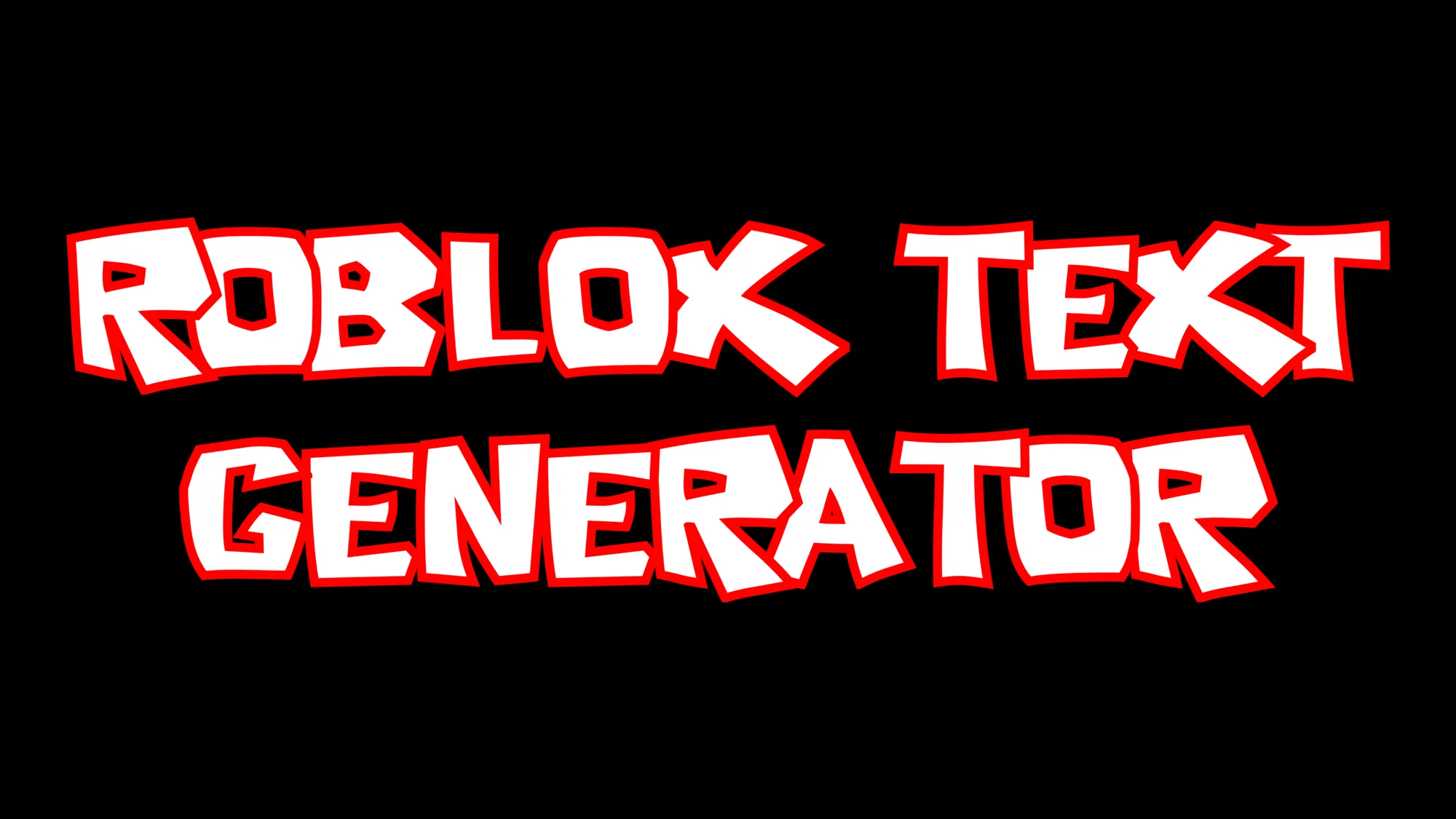
Il logo di Roblox è uno dei simboli più riconoscibili nel mondo dei videogiochi: deciso, divertente e pieno di energia. Con il giusto font Roblox e qualche effetto di testo creativo, puoi disegnare il tuo nome, logo o titolo nello stesso stile giocoso. Scopriamo insieme i design di testo ispirati a Roblox più popolari che puoi creare online.
Classico stile Roblox rosso
Il look classico di Roblox si distingue per le lettere bianche e spesse con un contorno rosso marcato. Questo stile del font del logo Roblox trasmette energia ed è immediatamente riconoscibile. È perfetto per banner, miniature di YouTube e loghi per i profili. Aggiungi un'ombra delicata o un contorno luminoso per dargli ancora più carattere.
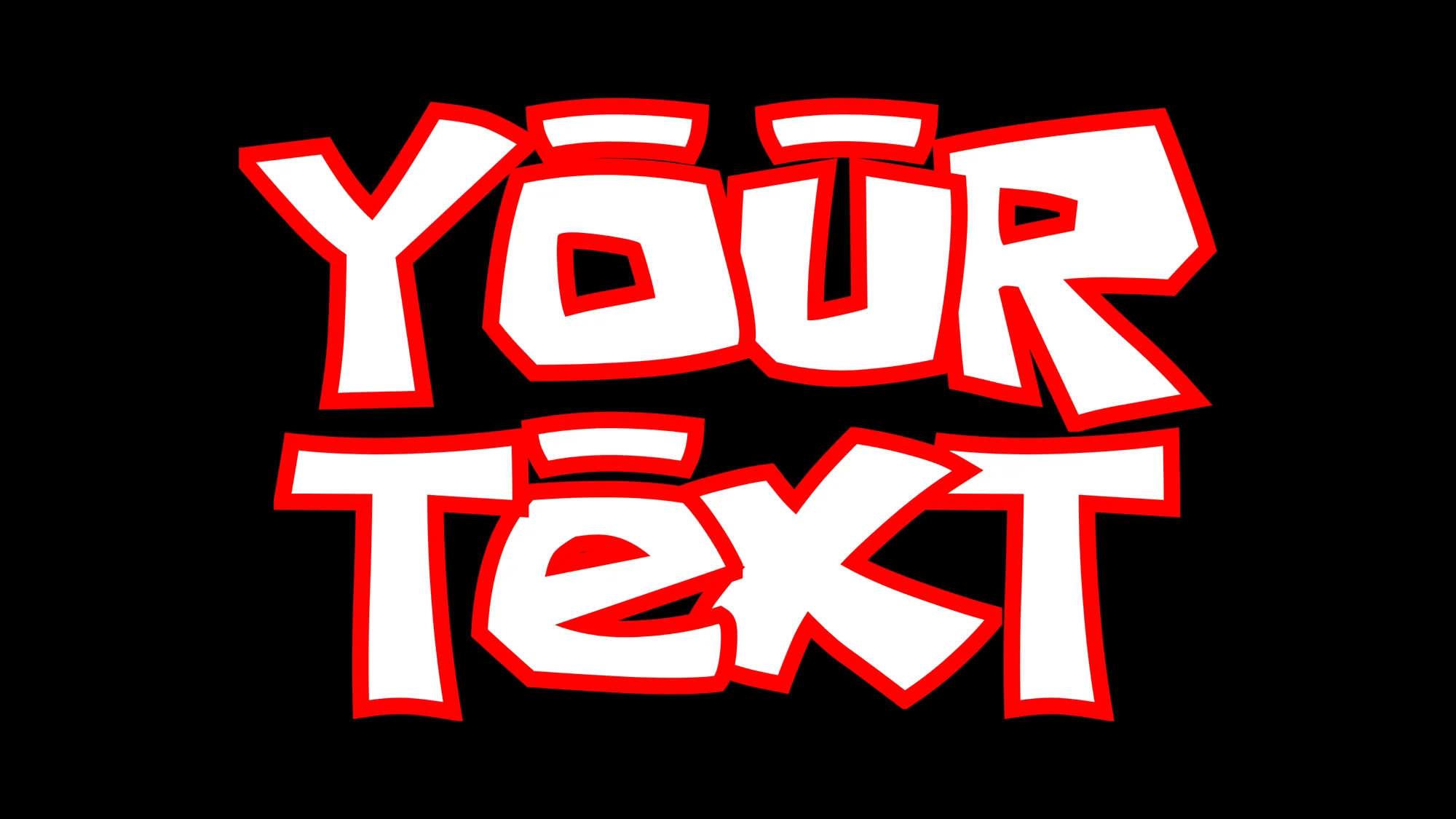
Che cos'era davvero il vecchio font di Roblox
Cerca il vecchio font di Roblox e troverai soprattutto file da scaricare, raramente una spiegazione. Eccola. Il logotipo del 2006 non è mai stato un font commerciale: era un lettering su misura, disegnato come logo e non come carattere, poi ripulito l'anno successivo in una versione vettoriale più ordinata. In seguito alcuni fan lo hanno ridisegnato e fatto circolare come file, da cui i nomi “2006 ROBLOX Logo” o semplicemente “Old Roblox Font”.
Questa storia spiega le forme. Un lettering da logo può permettersi di essere spesso, inclinato e un po' irregolare come nessun vero carattere potrebbe, perché doveva scrivere una sola parola. L'interfaccia è poi passata a un lineare geometrico pulito, ed è proprio questo contrasto a far leggere le forme antiche come retro.
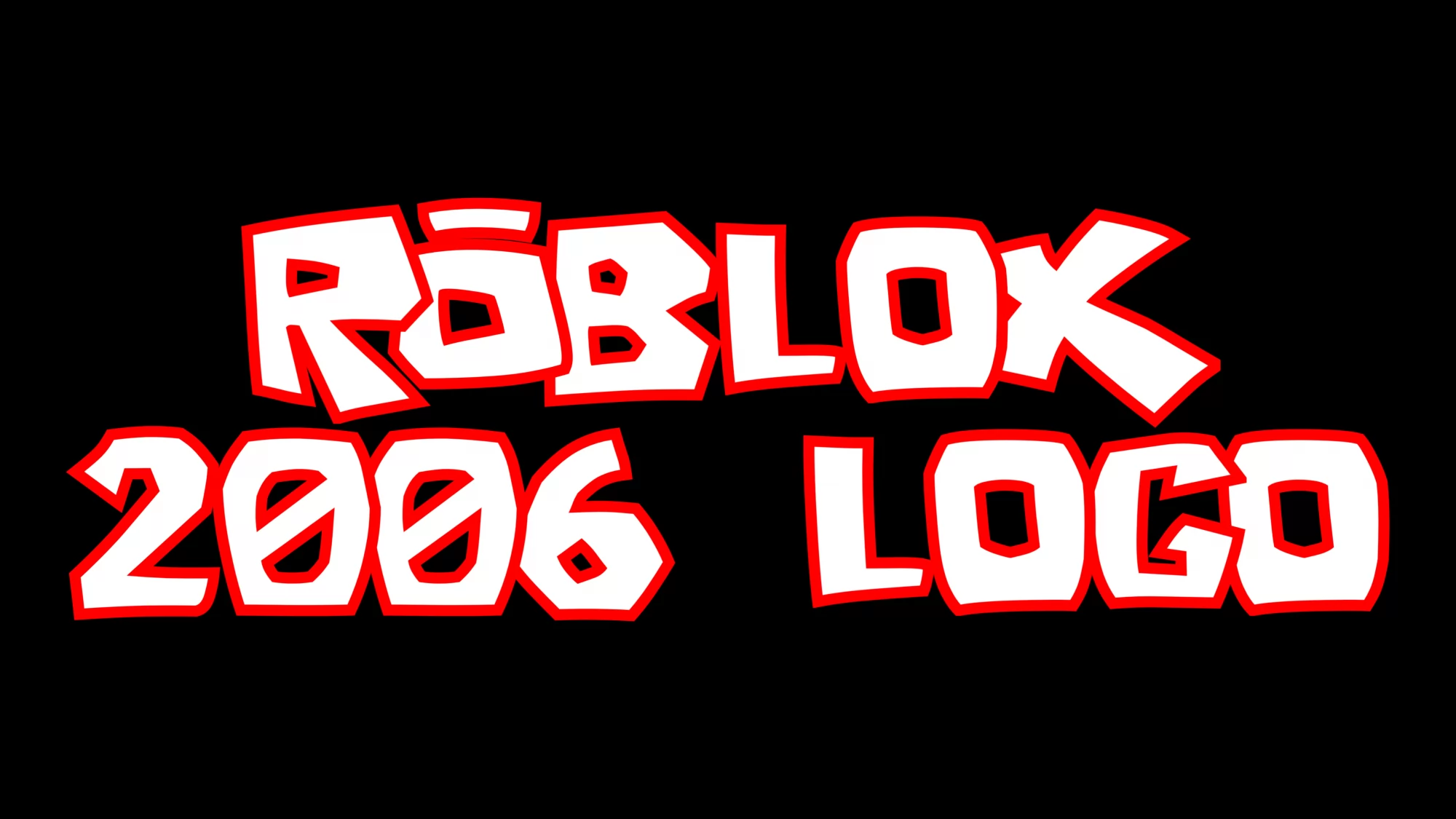
Non serve il file originale per ottenere l'effetto. Quattro cose lo reggono: lettere spesse che sembrano tracciate a mano più che composte, un contorno rosso robusto attorno a un riempimento bianco, linee di base che si rifiutano di restare dritte, e una leggera inclinazione su ogni carattere. Tieni il contorno spesso, perché è quel bordo rosso a tenere insieme le forme su uno sfondo affollato. Il generatore del logo 2006 monta tutti e quattro in un colpo solo.
Font Roblox 3D metallico
Per un effetto più moderno e curato, prova l'effetto di testo Roblox 3D. La finitura metallica e la leggera profondità rendono le lettere potenti e professionali, ideali per copertine di giochi, schermate introduttive o fan art. Abbina tonalità argento o grigie a sfondi blu acceso o rosso per richiamare i colori iconici del gioco.
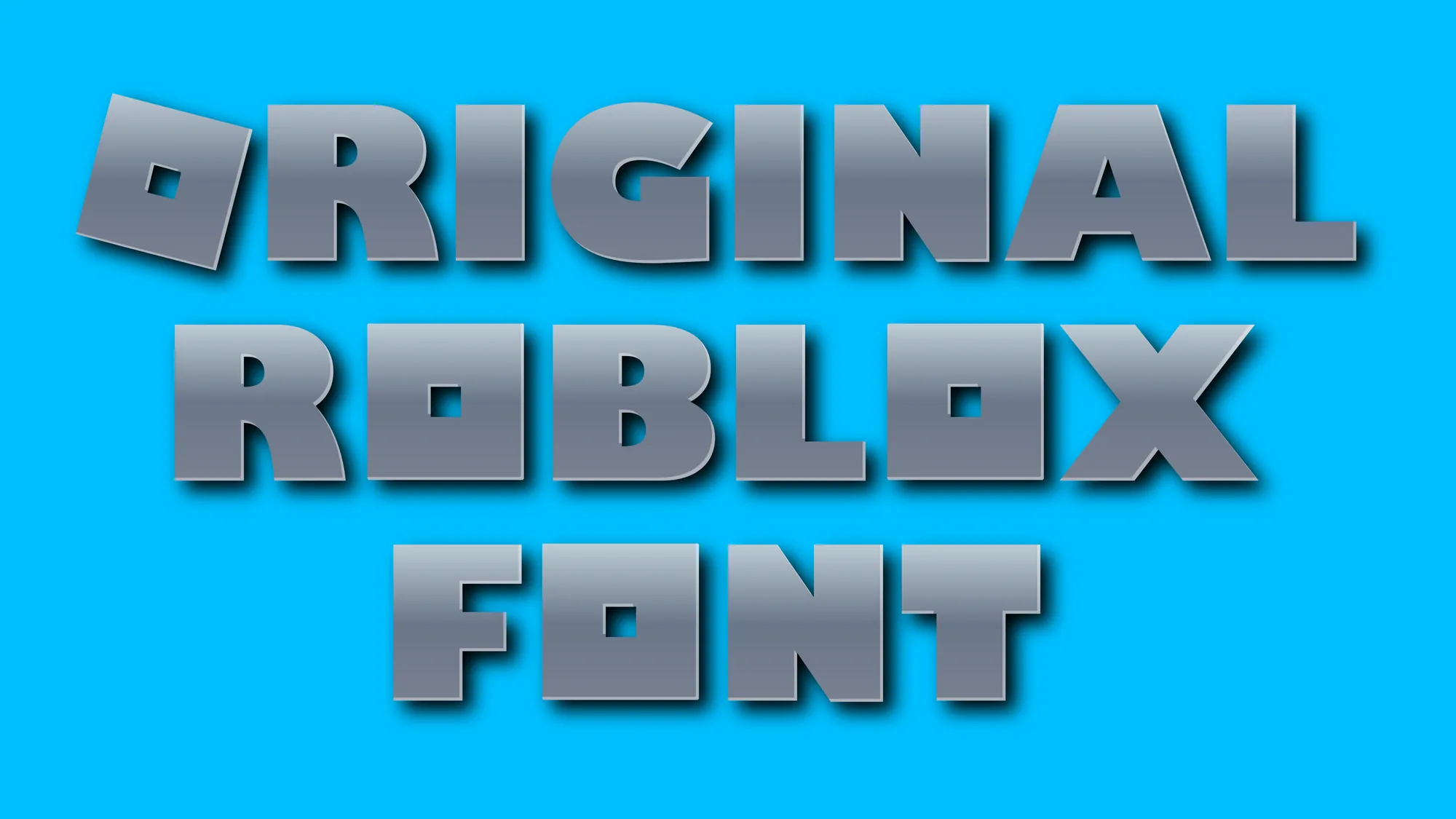
Testo Roblox in stile cartoon e con contorno
Una variante più leggera e giocosa utilizza lettere disegnate a mano con bordi bianchi decisi e un contorno rosso. Questo font Roblox in stile cartoon è ideale per i creativi che cercano qualcosa di divertente ed espressivo. È perfetto anche per dare personalità al tuo nome utente o alle schermate dei titoli.
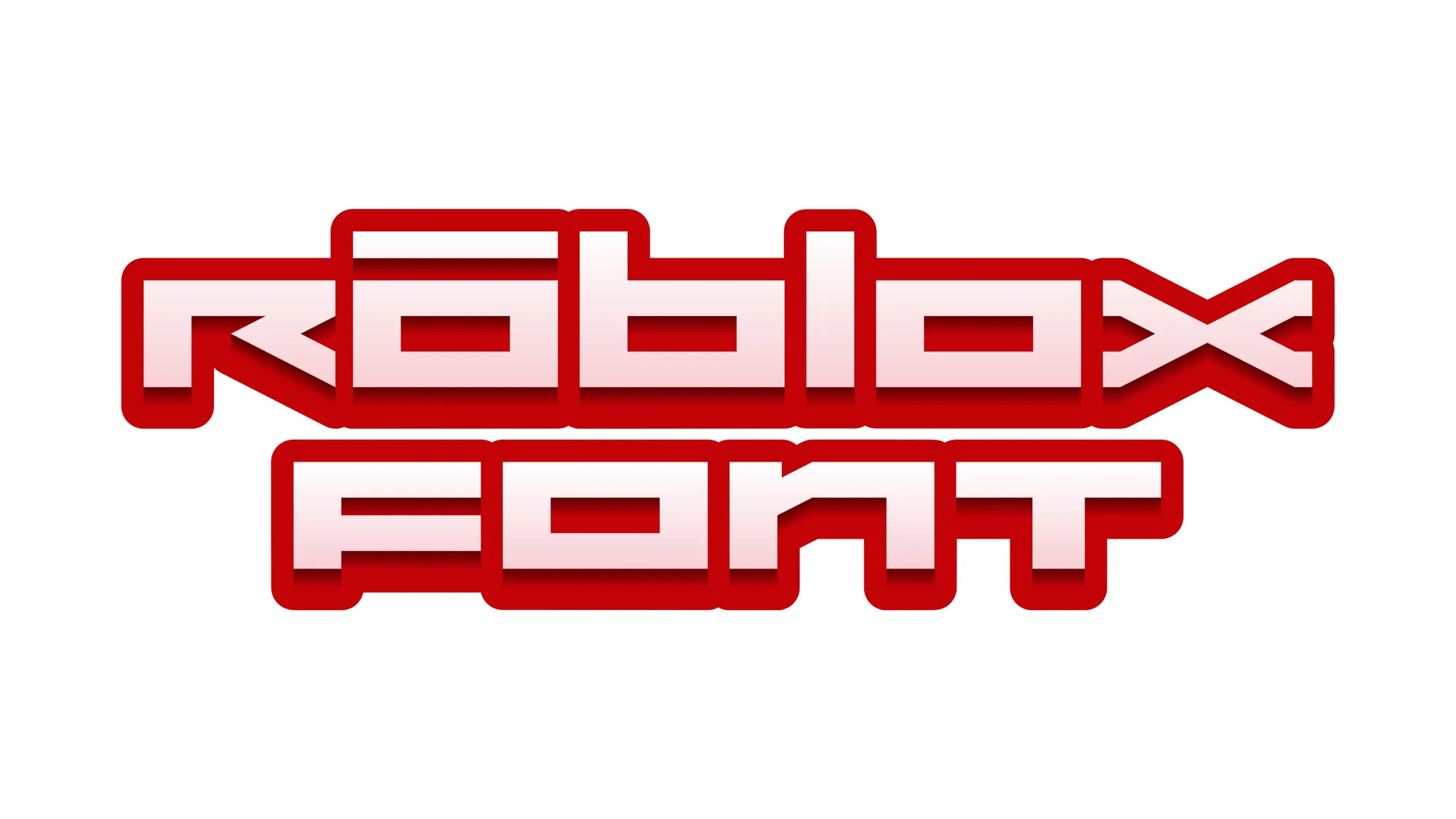
Effetto di testo Roblox animato
Dai vita al tuo design con il movimento. Un effetto di testo Roblox animato aggiunge transizioni luminose, capovolgimenti o rotazioni che risultano fantastici nei video brevi o nelle intro dei giochi. Anche le animazioni più semplici possono far risaltare il tuo logo Roblox e renderlo più dinamico.
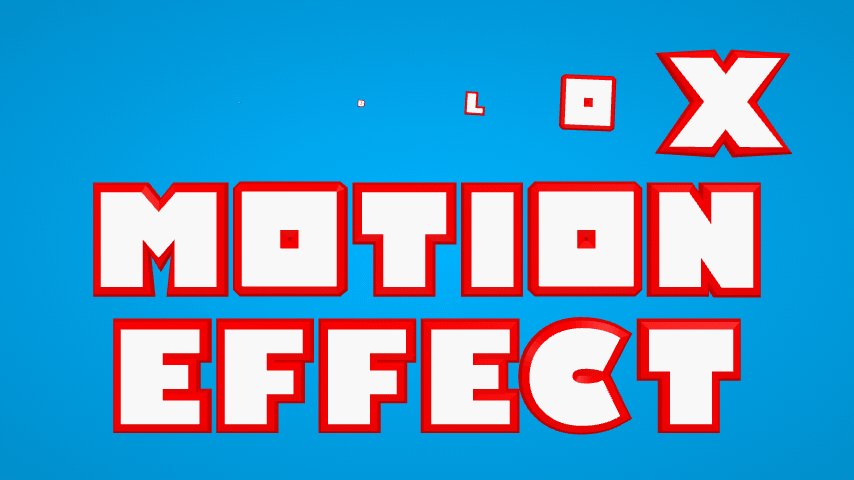
Look Roblox minimal e moderno
Per un aspetto più pulito e aggiornato, prova lo stile del branding attuale di Roblox: lettere rosse piatte su uno sfondo chiaro, con un font sans serif geometrico e deciso. Questa versione minimalista appare professionale e si adatta a qualsiasi formato, dai banner dei siti web alla grafica stampata.
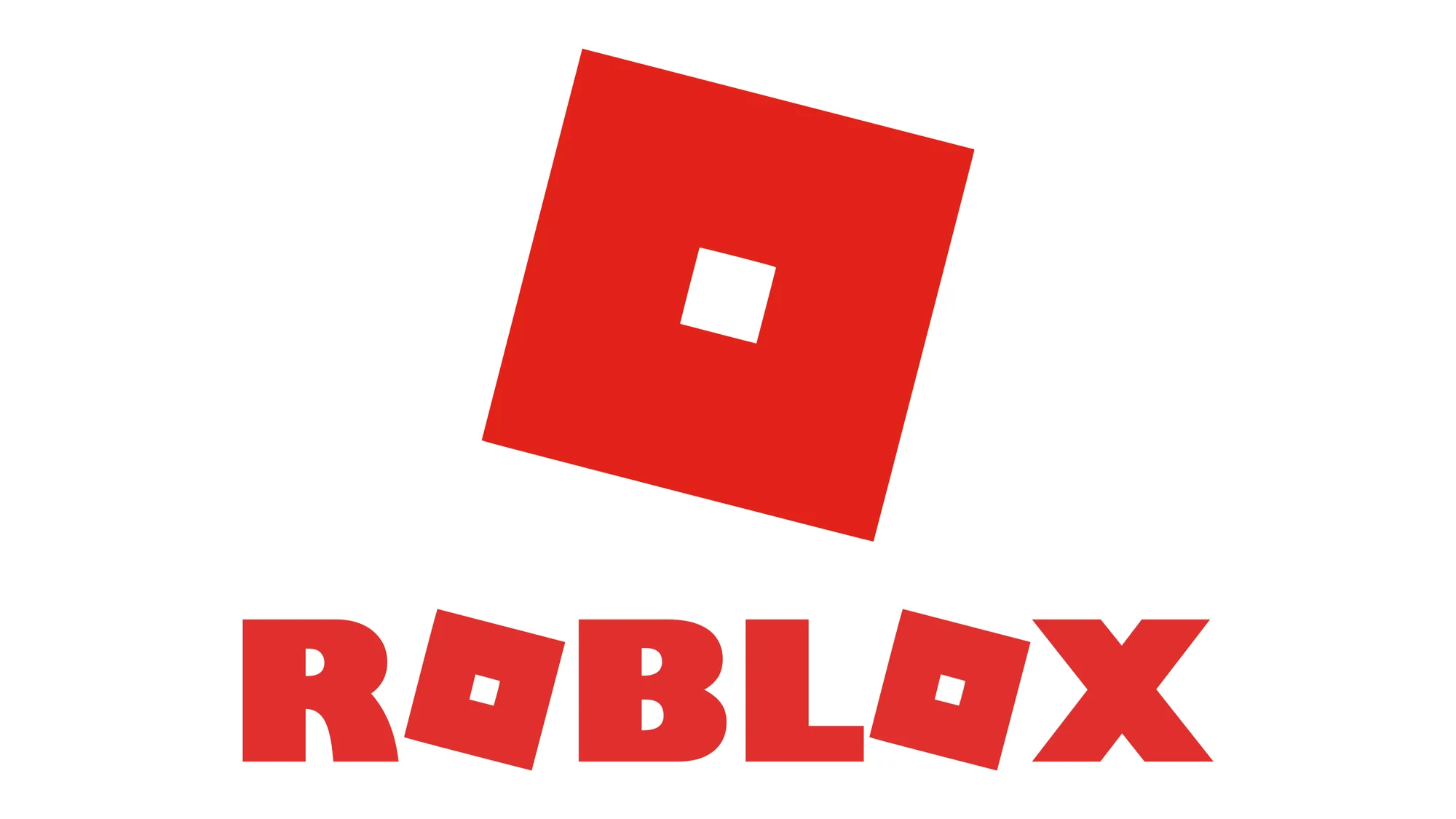
Conclusione
Dai loghi rossi classici ai moderni effetti 3D, i font Roblox ti permettono di esprimere la tua creatività con stile. Ogni versione cattura un lato diverso dell'universo Roblox: giocoso, futuristico o minimal. Sperimenta con texture, contorni e animazioni per trovare il look che si adatta al tuo mondo.